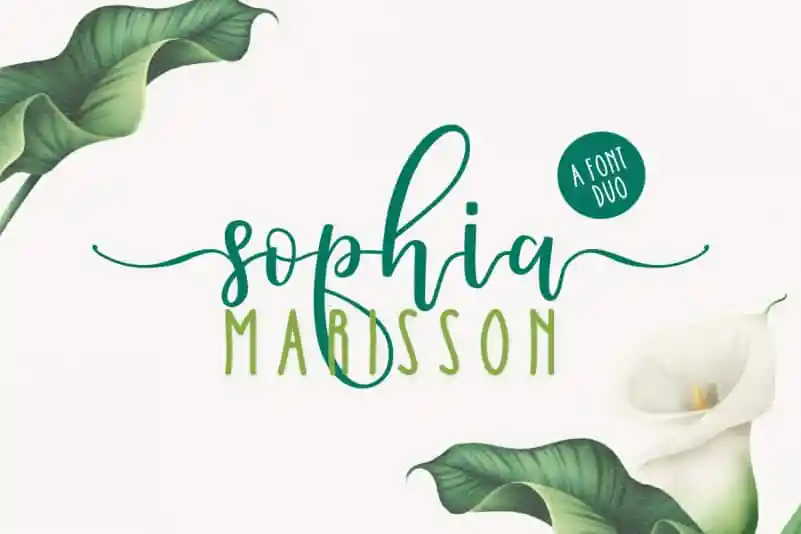
Sophia Marisson Script Font Duo – Download Grátis
Sophia Marisson Script Font Duo é uma combinação perfeita que parece ter saído diretamente do coração das mãos do designer. Esta fonte escrita a mão é ideal para todas as suas ideias de logomarca, branding e projetos DIY criativos. Ela traz um toque único e autêntico ao seu trabalho final, tornando-a perfeita para uma variedade de aplicativos digitais e impressos. Ideal tanto para criações digitais como físicas, o Duo da Sophia Marisson Script captura a essência do design à mão. Essa fonte é perfeitamente adaptada para uso em qualquer projeto que precise de um toque autêntico, seja uma identidade visual robusta e moderna ou detalhes adoráveis em projetos DIY. Sua caligrafia cuidadosa e delicada é a escolha ideal para quem busca uma fonte escrita a mão com estilo único, capaz de destacar sua marca.